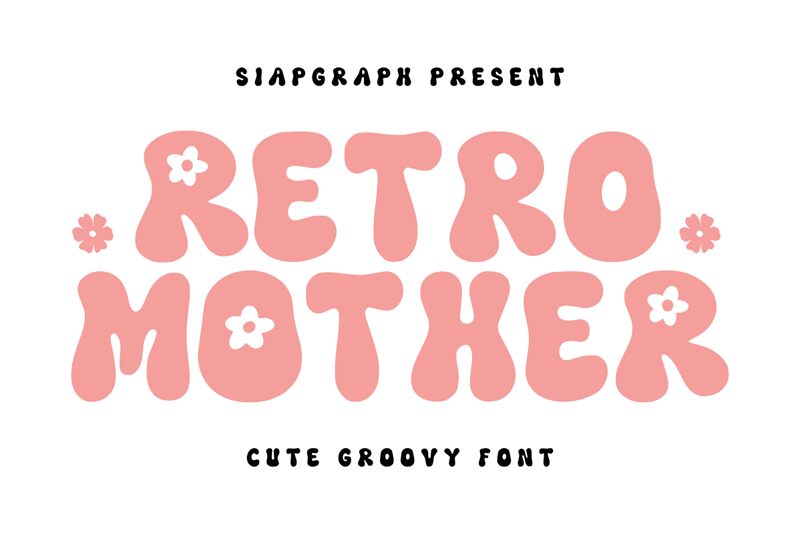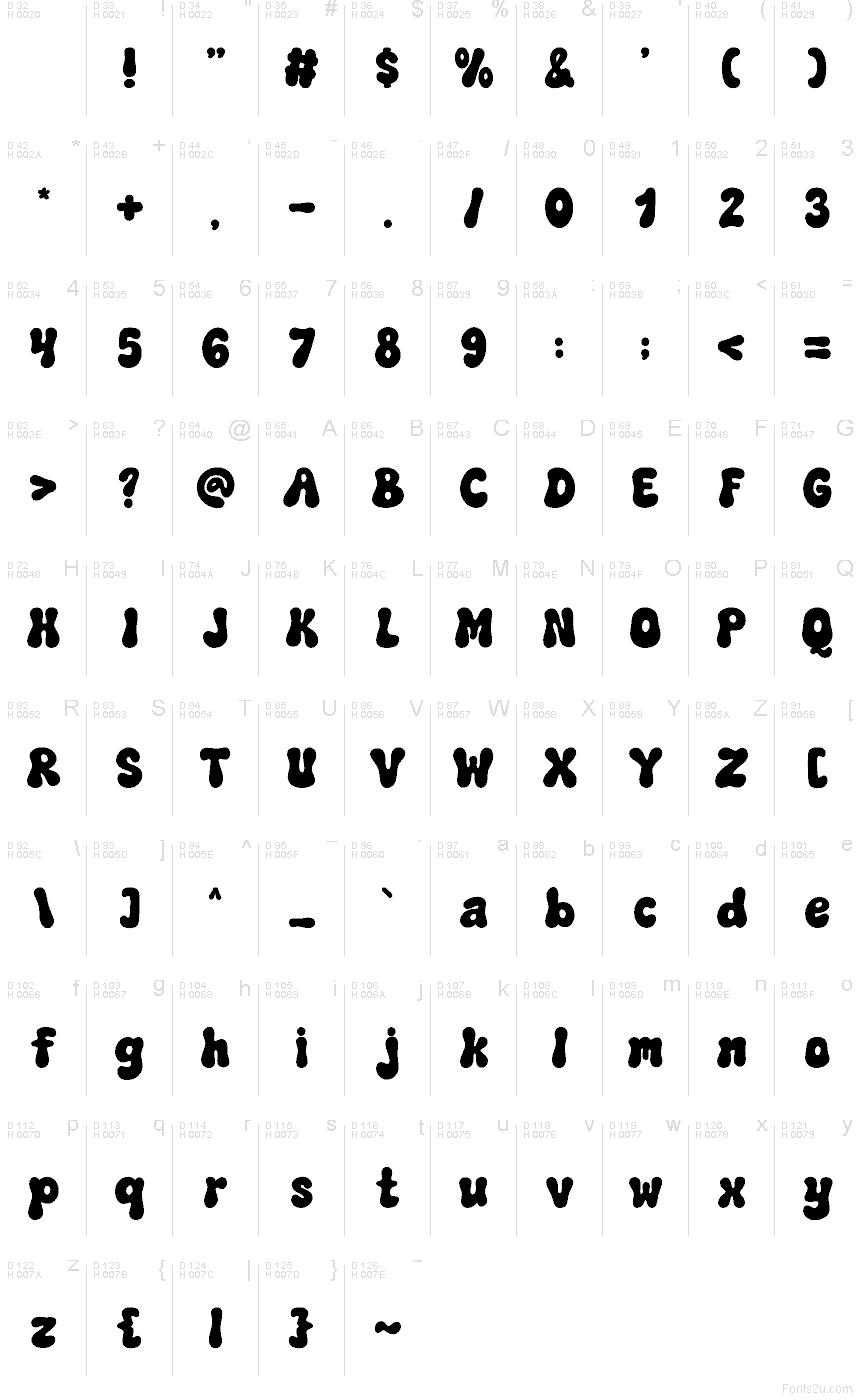
Retro Mother Regular
Retro Mother da SiapGraph é uma fonte display gratuita e groovy, com o formato das letras suaves e infladas da estética pop dos anos 70. Sua silhueta bulbosa e espaços internos estreitos dão ao texto um balanço descontraído, fazendo com que a tipografia pareça fofa e cheia, em vez de apenas arredondada.
Esse contorno inflado funciona perfeitamente em pôsteres musicais, identidade visual de cafés, adesivos, flyers de eventos e embalagens que buscam um toque vintage e acolhedor. Títulos curtos e logotipos aproveitam melhor seu estilo, especialmente onde as formas volumosas criam um bloco de texto compacto e amigável.